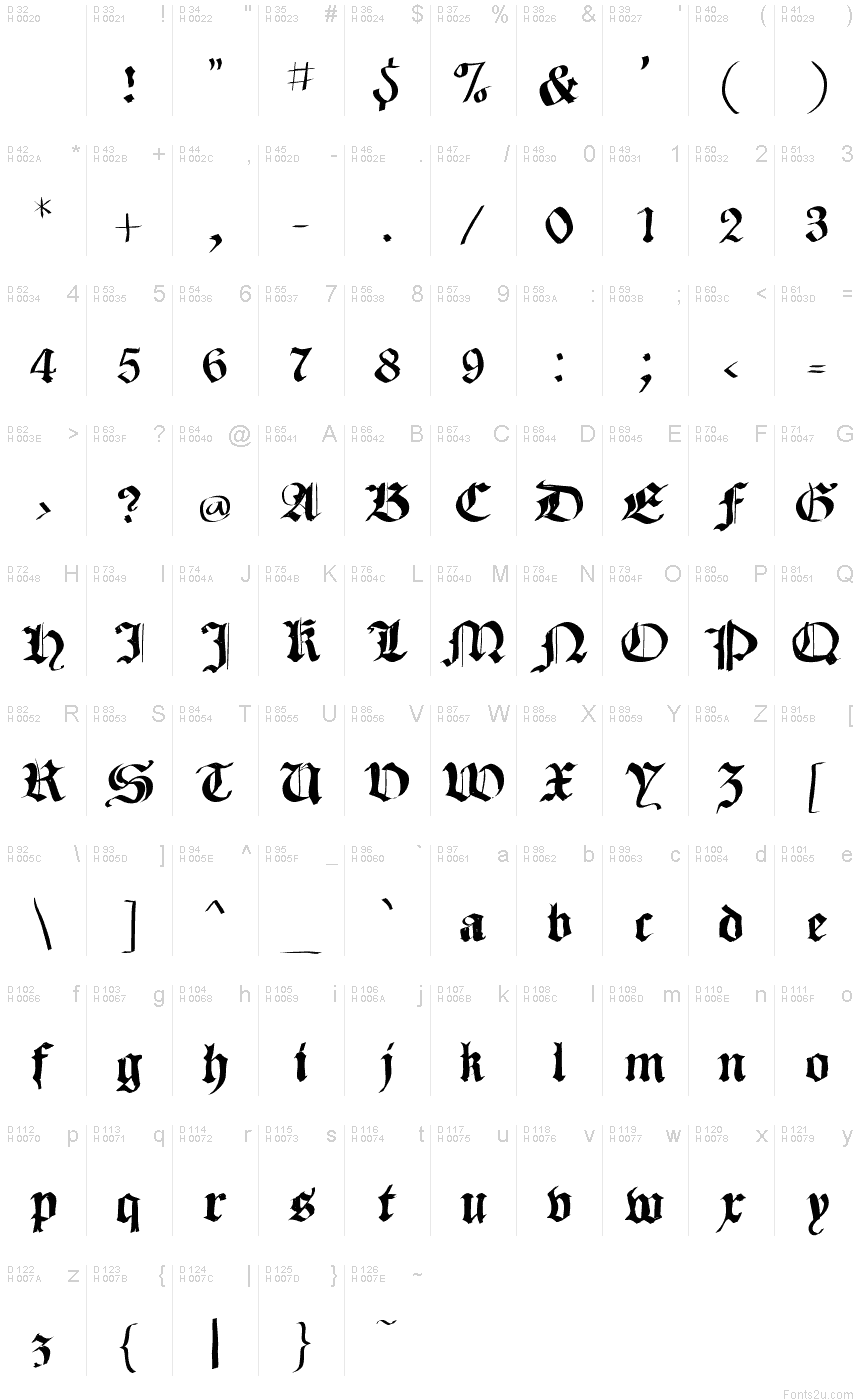
SketchedCassiusBroken
Sketched Cassius Broken, autorstwa Manfreda Kleina, to bezpłatny, średniowieczny gotycki krój pisma o ostrej, poszarpanej fakturze, przypominającej pismo ręcznie wyryte w drewnie. Litery opierają się na kolczastych kątach, nacięciach i zawijanych pociągnięciach, a szerokie otwarcie litery S nadaje całemu krojowi niespokojnego, starodawnego dramatyzmu, zamiast schludnego, kaligraficznego wykończenia.
Sprawdza się w tytułach plakatów, okładkach książek, identyfikacji wizualnej pubów, grafikach festiwalowych i tytułach gier, gdzie surowy, historyczny klimat liczy się bardziej niż gładkość. Jako darmowy font, świetnie nadaje się również do krótkich nagłówków i inicjałów w stylu monogramów, ponieważ poszarpane krawędzie i haczykowate kształty nadają nawet kilku literom mnóstwo klimatu.